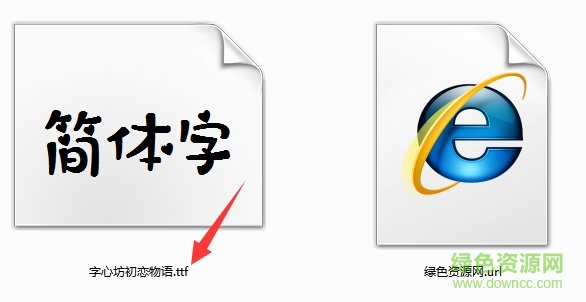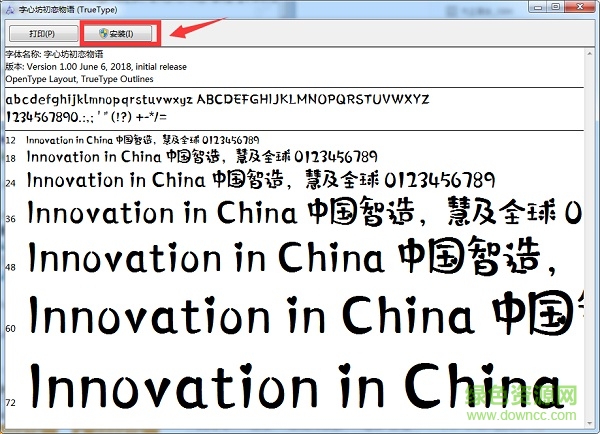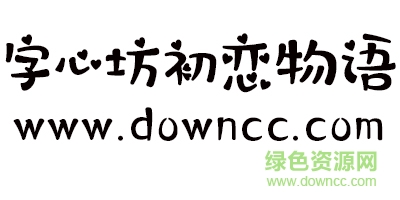
字心坊初戀物語字體是小編比較喜歡的一款卡通字體。字體看起來俏皮靈動(dòng),適合設(shè)計(jì)一些卡通類海報(bào)、報(bào)刊等!本字體支持phootpshop、word軟件安裝使用。歡迎下載。
字心坊初戀物語 Regular Version 1.00 June 6, 2018, initial release字體(字體家族名稱:字心坊初戀物語;字體風(fēng)格樣式名稱:Regular),共有7784個(gè)字符。
字心坊初戀物語字體字體字形設(shè)計(jì)萌動(dòng)童趣,結(jié)構(gòu)圓潤可愛,字形活潑清新,造型生動(dòng)有趣,具有靈活的適用性,婉約俏皮又不失時(shí)尚感!喜歡本字體的小伙伴馬上來綠色資源網(wǎng)下載吧。